Windws
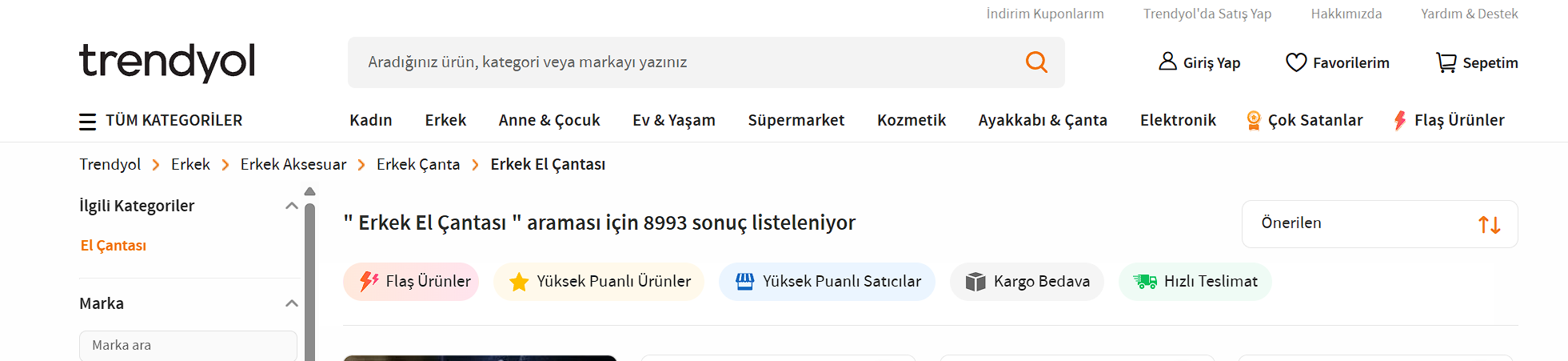
Macos
Resimlerde görebileceğiniz üzere başka birçok yerde de görebilirsiniz de ben örnek olması açısından attım.
Windows resminde mesela arama çubuğuna bakın "AradıĞınız ürün, kaTEGori veya markAyı yazınız"
yukarı sağ üstte indirim Kuponlarım
Aşağıda Slug'da çatlamalar, sağda sıralama ayarındaki Önerilen yazısının çatlaması, alttaki Flaş ürünler yazısındaki çatlamalar vs.vs. sayılamayacak kadar font bozukluğu var,
Windowsun birçok yerinde durum böyle sadece sitelerde değil.
Ve bence windows da bunun farkında zira 11'den sonra bazı yerlerde düzeltmeye gittiler ama hala %90 böyle.
Mesela:
- Bu bilgisayar yazan yerler ve bu bilgisayar klasöründe yazan yerler kusursuz, ama alttaki yerel disk, soldaki yazılar vs. hala eskisi gibi.
Bunu düzeltmenin bir yolu yokmu?